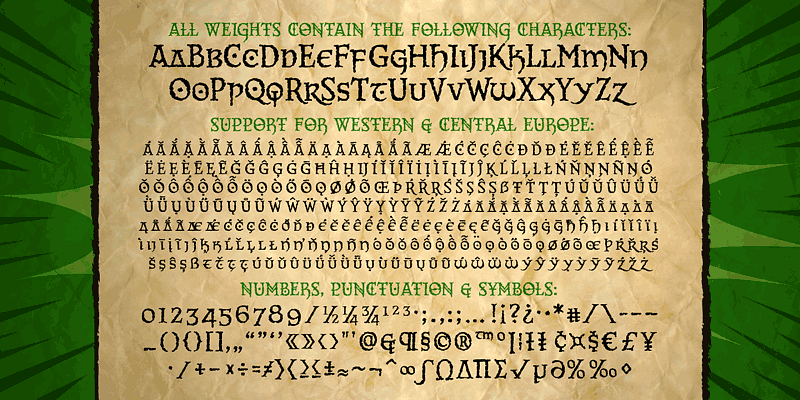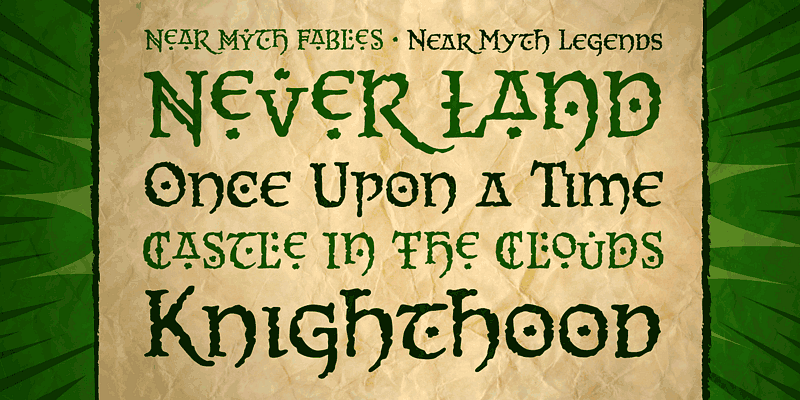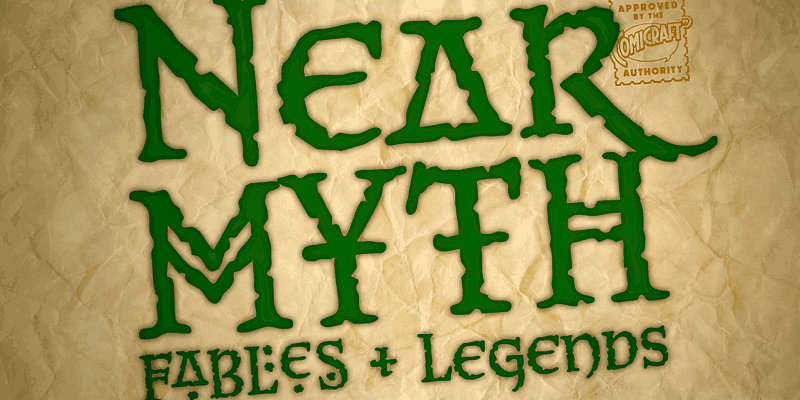
¡Los mejores tipos de letra para cómics del mundo! Después de haber dedicado cuerpo y alma para crear diferentes estilos de letra para miles de cómics, las Fearless Fonts de Comicraft irrumpen como la solución revolucionaria para videojuegos, series de televisión, títulos de películas y allá donde se necesiten unas fuentes animadas y divertidas.
En 1992, la pareja de talentos formado por Richard Starkings y John Roshell, junto con el equipo Fearless Fleet of Font Finaglers, empezó su andadura incorporando diseños únicos y tipografías de calidad al mundo de los cómics, la televisión y los videojuegos. Hoy en día son ampliamente conocidos por ser pioneros en el arte de la rotulación para cómics por ordenador.
Atrapadas en un mundo ajeno a ellas, las Fearless Fonts de Comicraft acudirán en tu ayuda en un abrir y cerrar de ojos.